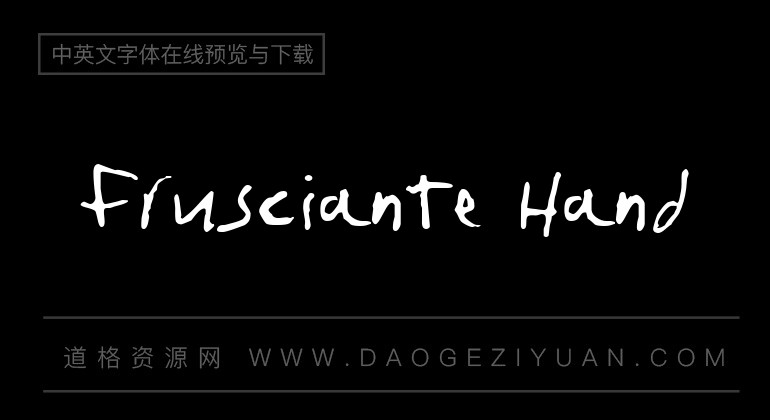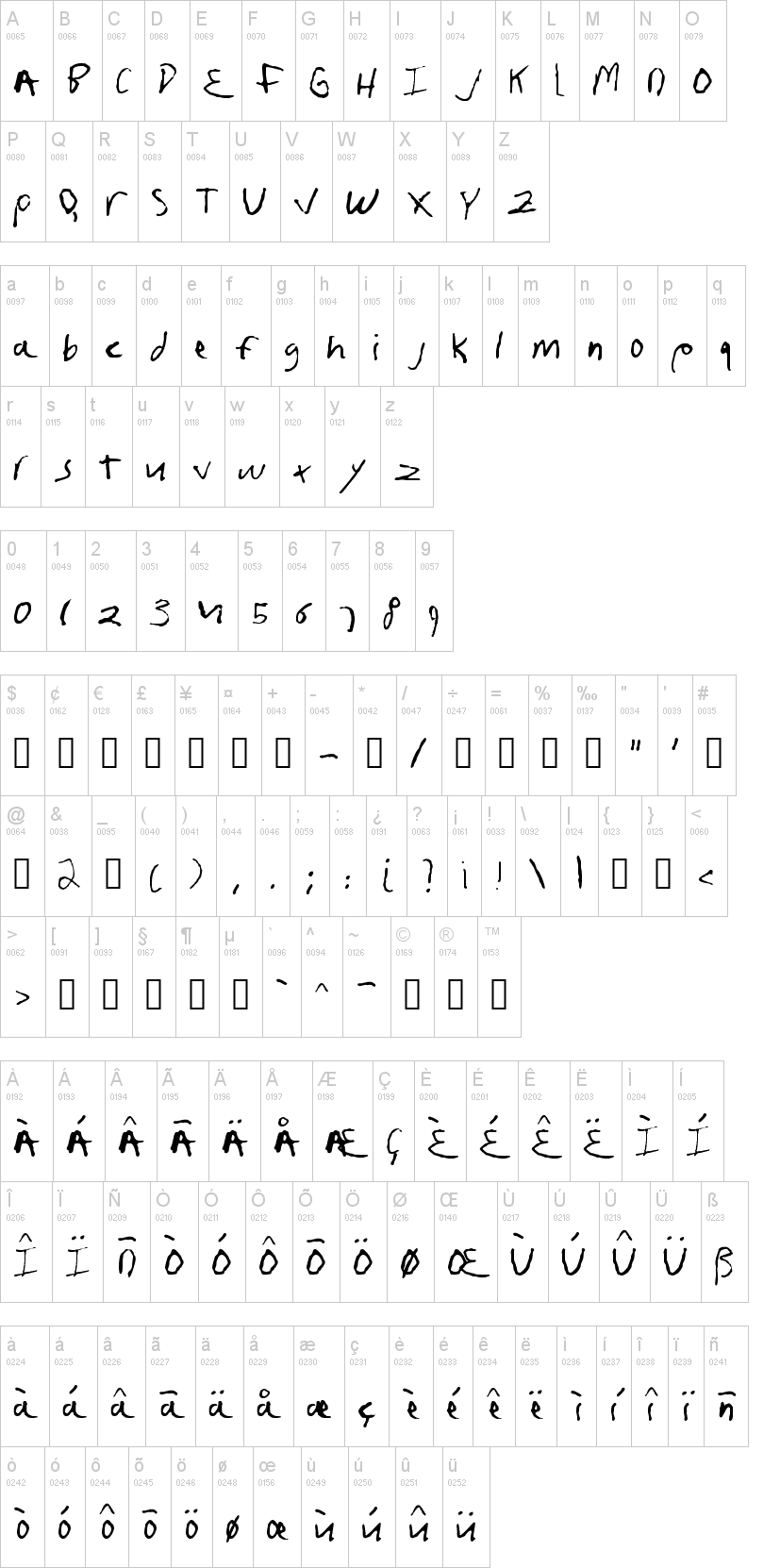
Frusciante Hand
? Frusciante Hand 字体是一款手写字体,由艺术家John Frusciante设计,它拥有温柔的曲线,而且有着独一无二的设计风格,可以帮助你创造出非常有趣的文字作品。它的特点是拥有细腻的线条,温柔的曲线,给人一种放松的感觉,可以用来制作海报、标志、网页等设计作品。
Frusciante Hand是一款非常不错的手写艺术字体,具有很好的视觉感,适合于文化类的宣传设计、商业类品牌的广告和产品包装设计以及个性化文字排版等较多场景。
Frusciante Hand字符映射图